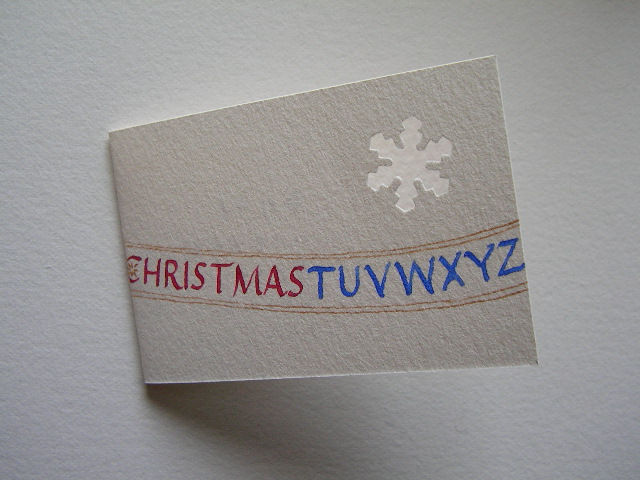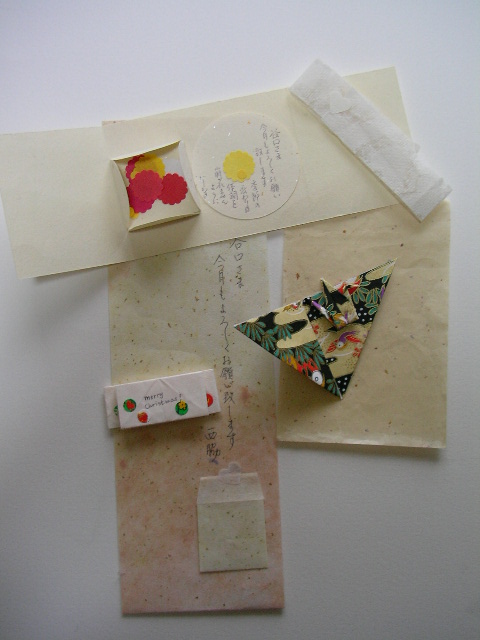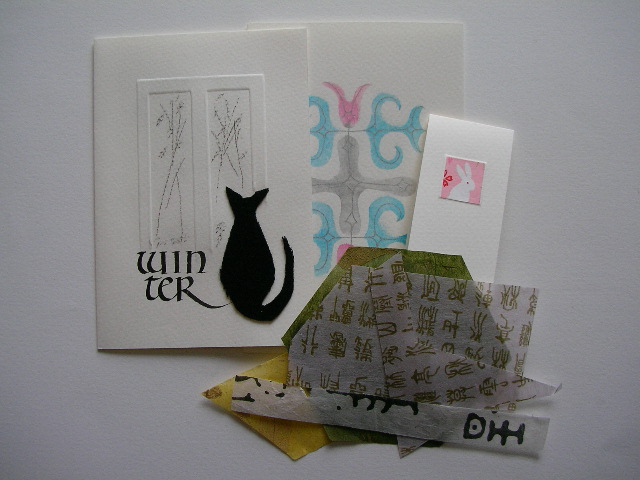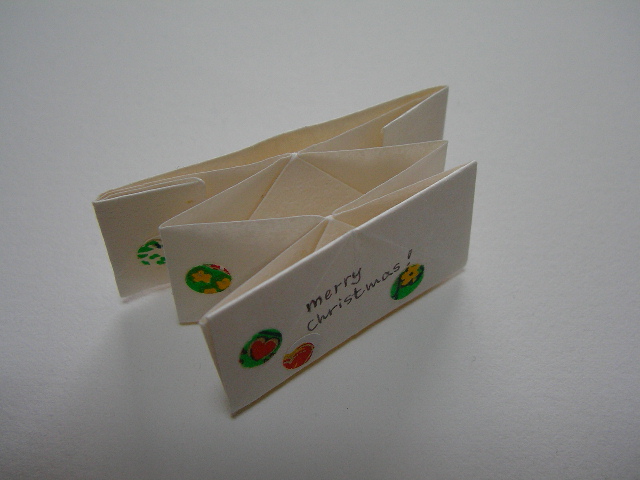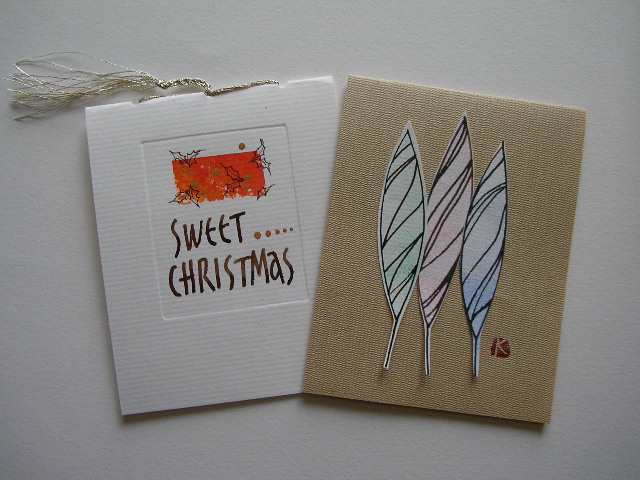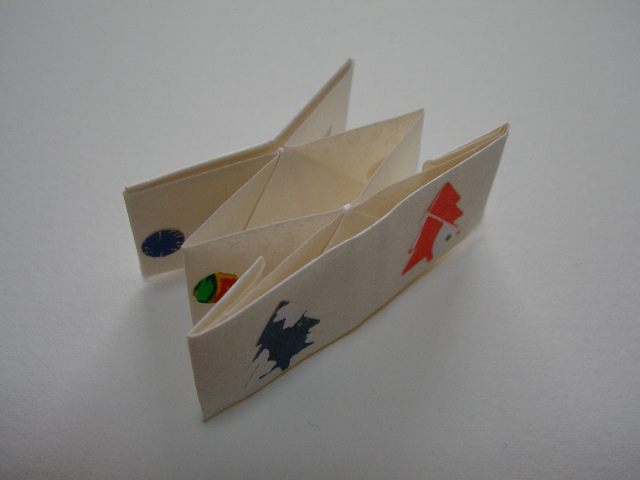
モジトルカードエクスチェンジ番外編
モジトルエクスチェンジの番外編です。毎月送られてくるカードに添えられているものをご紹介します。個性ひかる数々です!!!!!!!
HNさんのカードは、和紙の素材感を生かしたものです。小さなものたちももちろん和紙。やさしい心使いが伝わる品の数々です。そして季節もきちんと意識されていて、その中で12月に同封されていた小さな折り紙は、クリスマスのツリーのようにも見えました。どれもかわいいものばかり〜
誕生日カード紹介でエンボスのカードを掲載しましたが、私の誕生日のためにも遅ればせながらと送って下さいました。とても硬い紙なのに、きれいに文字が浮き出ています。硬質な紙ゆえ、Bはゴールドに彩色されたものを貼り合わせてボリュームを出す工夫をされたのではないでしょうか?!Nさんは、日本の古い切手をカード作りにうまく取り入れてもいます。センスがいいなあと感心しきりです。
KYさんからの同封のものです。毎回、モジトル宛以外のカードは見れないわけですが、KYさんは、いろいろなタイプのカードを作っていらっしゃると勝手に想像しております。かわいいもの、シックなもの、ポップなもの、洋から和まで。経験の広さと深さをしっかり自身の個性とブレンドして感心しきりです。手を動かしているのがとてもすきなんですよね〜きっと!
MNからの同封のもの、というより私ために作っていただいたカードです。はじめに韓紙が同封されていました。これを使ったカードも作られているのでしょう。和テイストでとおすのかなと思っていたら、そればかりではありませんでした。猫のついたカードは、お誕生日にいただいたものですが、シックでモダンなものです。毎回締め切りよりずっと早く一番の届くのが印象的!いつも元気なMNさん、戻ったらまたお便り下さいね!
NEさんからの同封のものです。NEさん切手同封ありがとうございました。
カリグラファーの手作りとは、小さな紙とペン、インクがあれば、このようなものが、すぐにできるものです。カリグラフィーをやっている原点を見る気がしました。NEさん、どうもありがとうございます。
カードは、小さな世界ですが、その人の持つ個性がでるものです。あと1回で終わるので、各人の手元には、12人のカードが並ぶわけで圧巻ですが、制作者の手元にも12種類のカードがそろうのではないでしょうか。叶うならば、全員の12種類並んだカードをみて見たいものですわ〜!
かわいいウサギさんのカードはどなたかべつの方のです・・・。